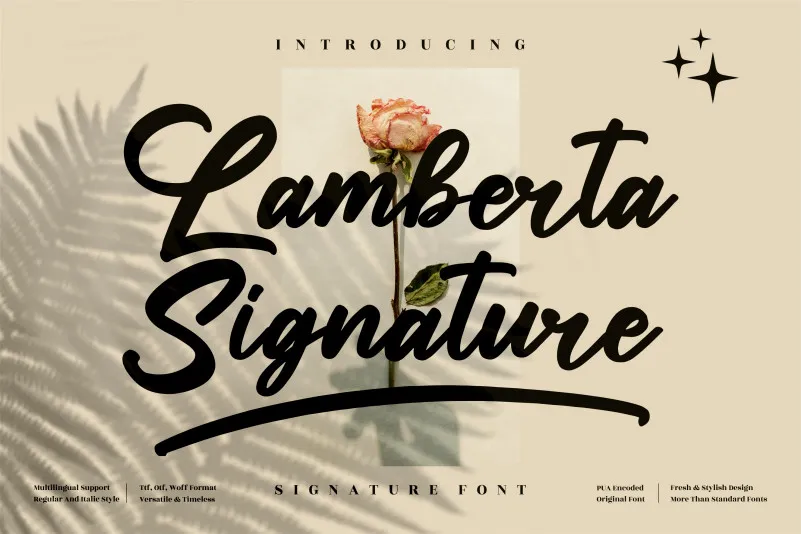
Lamberta Signature Font – Download Grátis
A Lamberta Signature Font é uma elegante escolha para quem busca dar um toque sofisticado a qualquer projeto visual. Esta fonte premium foi projetada para atender aos mais exigentes requisitos de identidade visual, desde a criação de logos e projetos de marca até o desenvolvimento de embalagens, materiais decorativos e outros itens que ganham vida em sua casa. Suas linhas fluidas e delicadas permitem personalizar seu design de forma única e criar um toque exclusivo que se destaca dos demais. Com aplicabilidade para uma ampla variedade de projetos, a Lamberta Signature é perfeita tanto para elementos visuais como para conteúdo textual. Ela pode tornar sua marca mais impactante em materiais de embalagem de luxo ou produtos personalizados, oferecendo um toque sofisticado e único que se destaca entre o concorrido mercado. Seja por meio de cartões de nome, cartas de convite, presentes personalizados, capas de livros ou até mesmo como um fundo para fotografia, esta fonte tem a capacidade de proporcionar um toque autêntico e sofisticado que se alinha perfeitamente com o mais alto padrão de design. Com ela em mãos, você pode projetar qualquer tipo de projeto desejado sem comprometer seu estilo ou elegância.